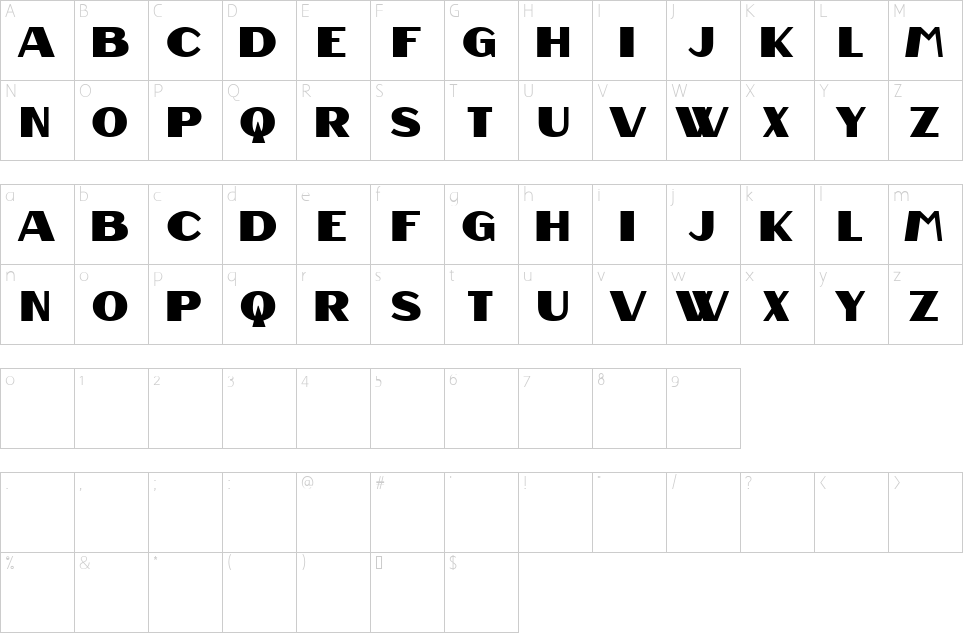
A Jangkar é uma fonte que traz a essência do design moderno e clean para projetos digitais. Desenvolvida pelo designer Vladimir Nikolic, a Jangkar é uma escolha perfeita para designers que buscam uma fonte com uma aparência atraente e versátil. Essa fonte foi projetada para ser fácil de ler em diversos tamanhos e é adequada para um grande número de aplicações, incluindo textos em sites, e-books, ou até mesmo para gráficos publicitários. Com sua natureza minimalista e versão gratuita para uso personalizado, a Jangkar oferece uma excelente maneira de adicionar um toque único e moderno a qualquer projeto. A fonte já foi baixada 1.220 vezes, o que mostra a sua relevância e popularidade. Descubra por si mesmo qual será sua próxima escolha de fonte com a Jangkar.